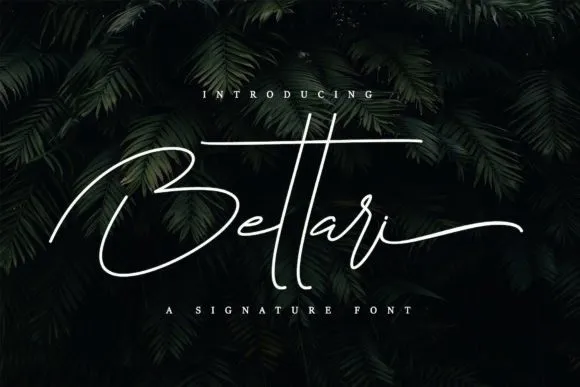
Bettari Font – Fonte Grátis
Bettari Font
A fonte Bettari é uma elegante escolha para aqueles que buscam personalidade em seus projetos digitais. Ela combina delicadeza e fofura, criando um efeito suave e alegre ideal para design de cartões de casamento, cartões de agradecimento, mensagens pessoais, logotipos ou identidades corporativas. Cada caractere é cuidadosamente detalhado, desde as letras maiúsculas até os números e símbolos. Suas características delicadas permitem uma apresentação única, tornando-a perfeita para dar um toque handwritten a qualquer projeto. Seja para criações de alta qualidade ou trabalhos pessoais, Bettari é uma fonte atemporal que se destaca em qualquer design.